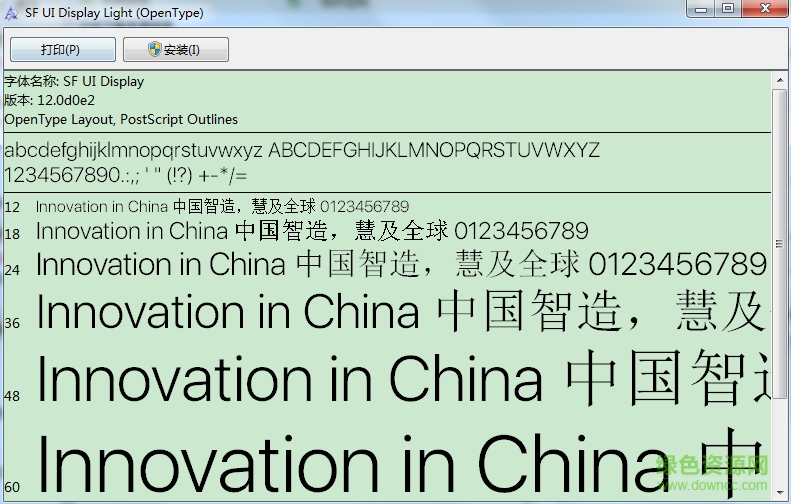
sfuidisplay light是一款非常漂亮的英文字體,這款字體線條粗細(xì)適中,字跡清晰,整體效果非常出色,喜歡這款字體的朋友歡迎來(lái)綠色資源網(wǎng)免費(fèi)下載使用。
這款字體結(jié)構(gòu)簡(jiǎn)潔,易讀性強(qiáng),擁有較為完整的詞庫(kù),非常適用于ppt、影視制作、廣告設(shè)計(jì)、宣傳海報(bào)等領(lǐng)域,歡迎大家來(lái)綠色資源網(wǎng)下載體驗(yàn)。